Eben auf Twitter gefunden: typografische Weltkarten, entworfen von Dirk Schächter. Sie wurden mit dem IF Design Award ausgezeichnet und sind nominiert für den Designpreis der Bundesrepublik Deutschland 2011. Die Typomaps sind von Hand gesetzt (Neue Helvetica Black Condensed), so dass eine verblüffende Übereinstimmung mit der konventionellen Weltkarte erzielt werden konnte. Es gibt zwei Motive, eines mit dunkelblauen und eines mit hellblauen Meeren. Als Poster (1000 mm x 700 mm) kosten sie, zweiseitig bedruckt und laminiert, 49 € inklusive weltweitem Versand. Zum Anfreunden bietet sich ein kostenloser Bildschirmhintergrund an. Bestellungen und Downloads auf www.typomaps.net.
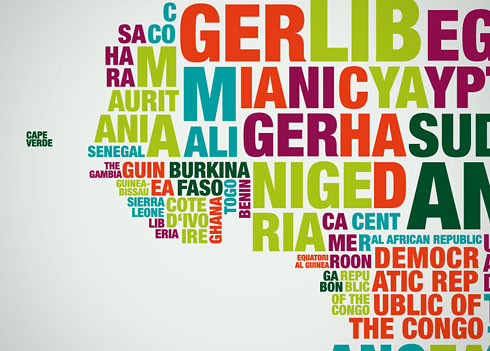
Erinnert mich stark an diese Grafik von Golden section Graphics für das Goethe Institut.
Genial!
Ganz toll!
Sehr cool, aber in Helvetica etwas langweilig. Und mit 49,- ein sehr stolzer Preis, da baue ich mir das lieber mit einer anderen Schrift nach und hänge es mir @home auf. Ist günstiger …
Unmöglich. Total grobschlächtig, schnell gemacht, komische Farben, alte Typo. Was daran genial sein soll weiß ich nicht. Ich denke das ist eher ein Versuch aus Schice Gold zu machen.
was wäre NICHT grobschlächtig?
was wären bessere farben?
es gibt sicher moderne (was ist ein moderner font?) schriften, die schmale helvetica ist allerdings schon ein schmuckstück.
schnell gemacht? okay meister aller klassen, dann stell ich mich neben dich und du baust das in 3h exakt so auf incl. zurichtung und ausrichtung an einem mit sicherheit sehr komplexen raster.
und last but not least: was hat ein begriff wie »shice« in einer sachlichen diskussion zu suchen? wir sind dich nicht in einem gangstervideo.
klingt eher nach großmaul denn nach können mr. isolight.
Grobschlächtig meint undetailliert.
Also ist das in 3 Stunden tatsächlich zu schaffen — allerdings nur wenn niemand schnaubend neben mir steht.
Das Raster wurde sicher nachträglich untergemogelt.
Besser Farben wären diese, welche ein Konzept vermuten ließen, eine gewisse Stimmung transportieren. Dies hier ist bunt.
Dass die Helvetica nicht besonders originell ist, brauch ich ja nun nicht weiter zu erklären. Ich nehme den Shice zurück und behaupte nun, das dies etwas ist was niemandem hilft und keiner braucht. Außerdem fehlt der Nordpol
Also die Karte ist wirklich schön. Und jede Schrift kann man langweilig finden. Helvetica hat da immer noch die Schutzfunktion, ein Klassiker zu sein.
Was ich aber immer weniger verstehe ist, warum manche Arbeiten einen Preis erhalten (oder dafür nominiert werden) und andere nicht. Da mag man mir jetzt Neid vorwerfen, aber ich wundere mich immer wieder.
Und zu den drei Stunden: Zum direkten Nachbauen würde mir das auch reichen. Zum selber entwickeln und in Produktion gehen niemals!
diese idee ist leider bereits viel zu oft gesehen und erschwerenderweise in deutlich ästhetischeren und konsequenteren umsetzungen (siehe paula scher)… was übrig bleibt ist also doch relativ willkürliche typo-dekoration, die ja durchaus ihre berechtigung haben darf. allerdings muss diese sich nicht über raue kritik wundern.
Zeig’ her! Das will ich optisch untermauert wissen.
Zu Paula Scher:
Mehr Kunst als Infografik, zwar schön aber auch: » … designed ist es erst, wenn man es nicht mehr lesen kann«.
Schade, ein Rechtschreibfehler bei Griechenland.
Die Farben bei dem mit blauem Hintergrund gefallen mir deutlich besser. Mal ein anderen Hintergund, nicht nur die schön raußgeschleckten Fotografien die kein bisschen Authentizität mehr besitzen.
Man sollte die Karte von Dirk Schächter auf keinen Fall mit der – Entschuldigung – naiven Technik von Paula Scher vergleichen. Der Witz liegt im vorliegenden Fall in der Reduktion, und nicht im Überfluss (wie bei Paula). Ob das große Russland oder das kleine Portugal – jedes Land ist nur aus seinem Namen gebaut, kein Buchstabe mehr, kein Buchstabe weniger.
Was die Zeit angeht … 3 h, ich möchte euch mal erleben, wenn ein Auftraggeber mit dieser Forderung an einen Designer herantritt. Laut Wikipedia setzt sich unsere Erde aus 193 Staaten zusammen. Lasst mich mal kurz rechnen:
1 Dokument aufbauen, Templates recherchieren und vorbereiten: 1 h
2 verschiedene Schriften ausprobieren: 1 h
3 Zeit für das Setzen des 1 Landes: ø 0,5 h
4 Zeit für das Setzen 192 Länder (ohne Farbgebung): 192 x 20 min = 64 h
5 Farbgebung: 8 h
Meine Schätzung für das Erstellen der Druckvorlage: 74,5 Stunden (ohne Fehler, Sackgassen, technische Pannen). Wenn mir ein Designer den Job mit 80 h kalkulieren und anbieten würde … no discussions, Zuschlag!
Jetzt würde mich natürlich mal interessieren, wie Dirk Schächter wirklich kalkuliert hat.
Verstehe auch nicht, was daran jetzt so toll sein soll…
ich habe mir zwar nun nicht alle kommentare durchgelesen, aber der name Mark Webber scheint hier noch nicht gefallen zu sein.
ein verrückter aus reading, england, der im linolschnitt einige typografische städtekarten anfertigte und mit der pariskarte sein meisterwerk schuf (leider wohl noch nicht gedruckt).